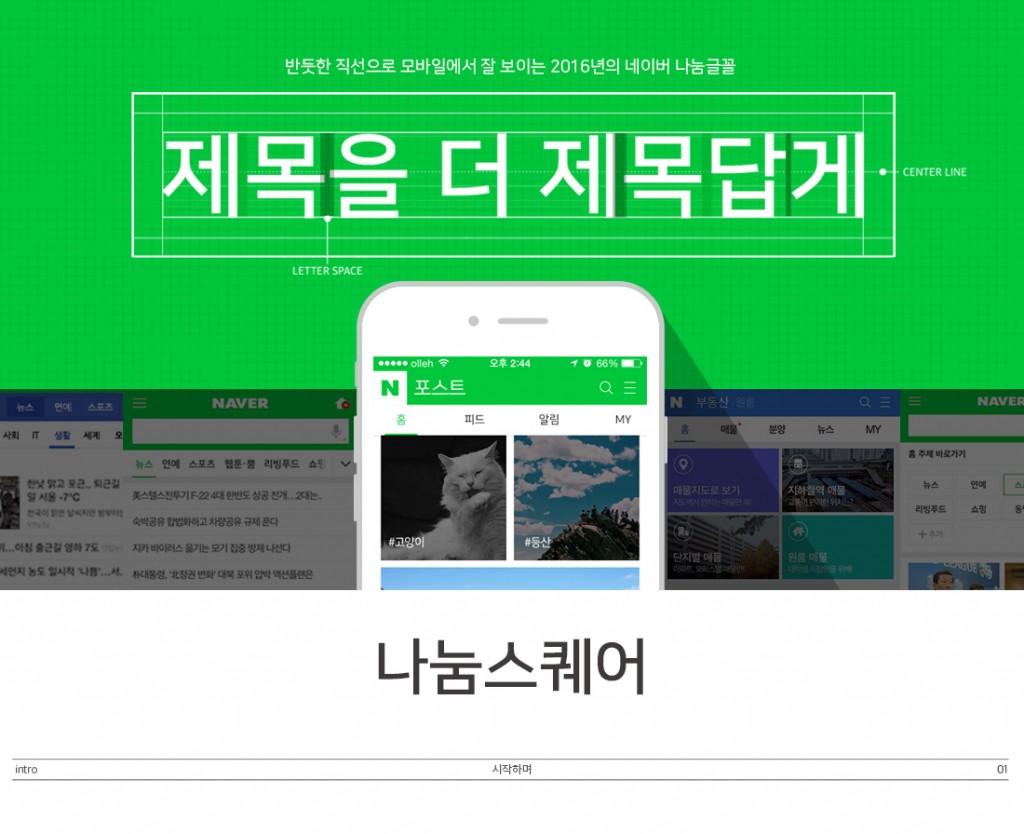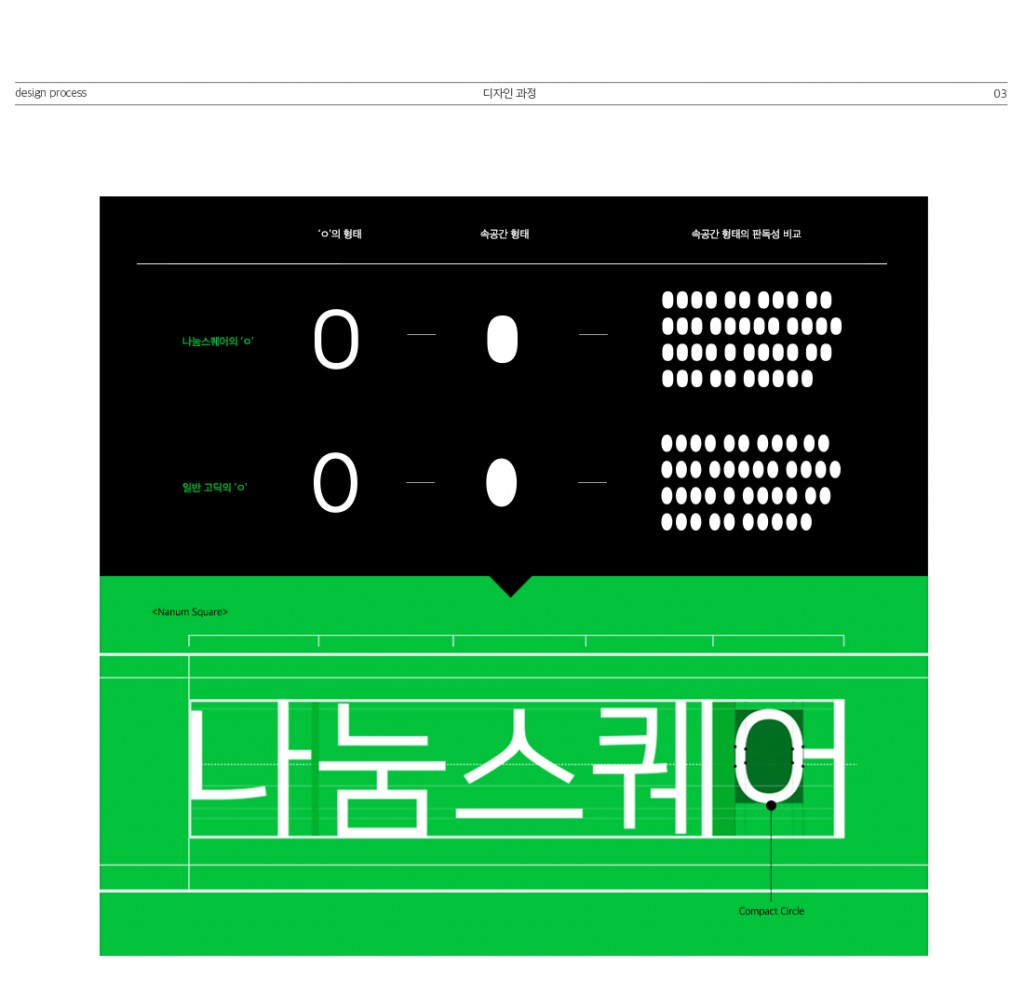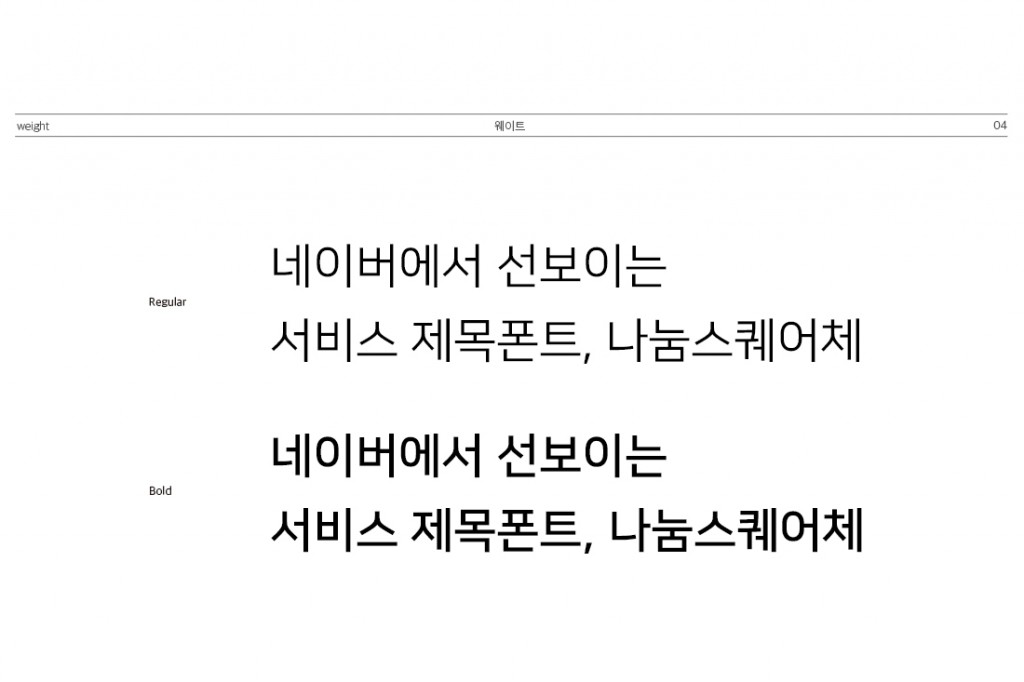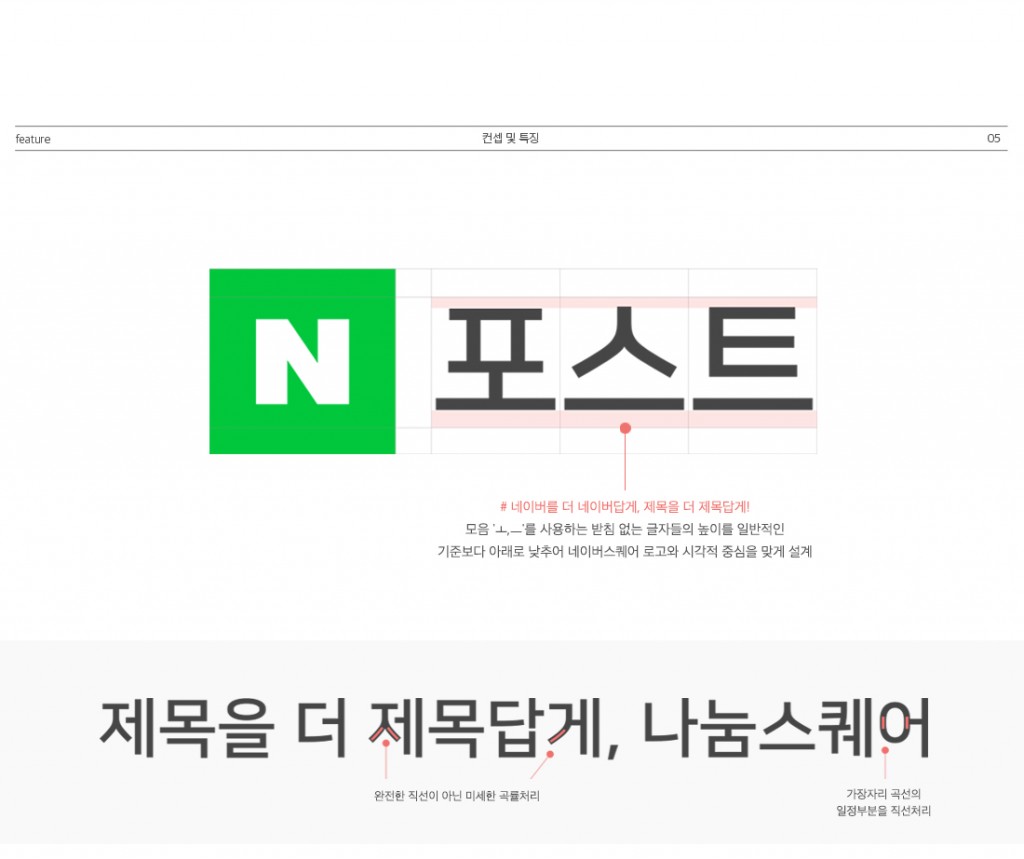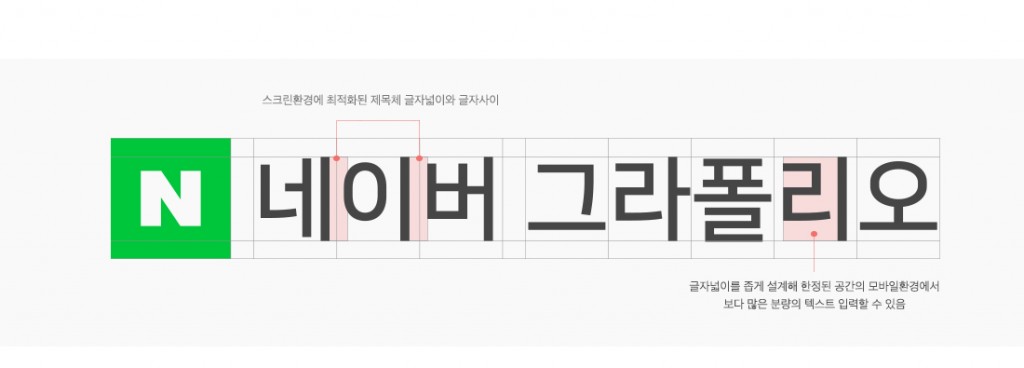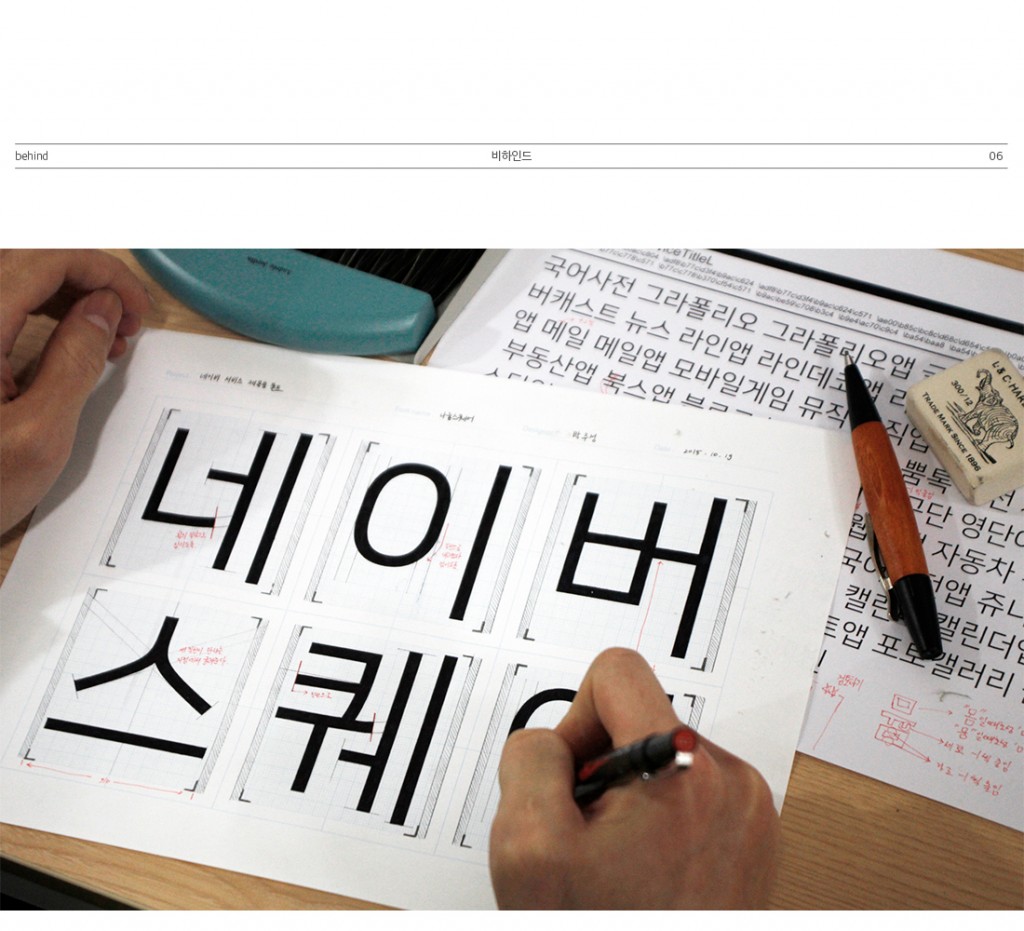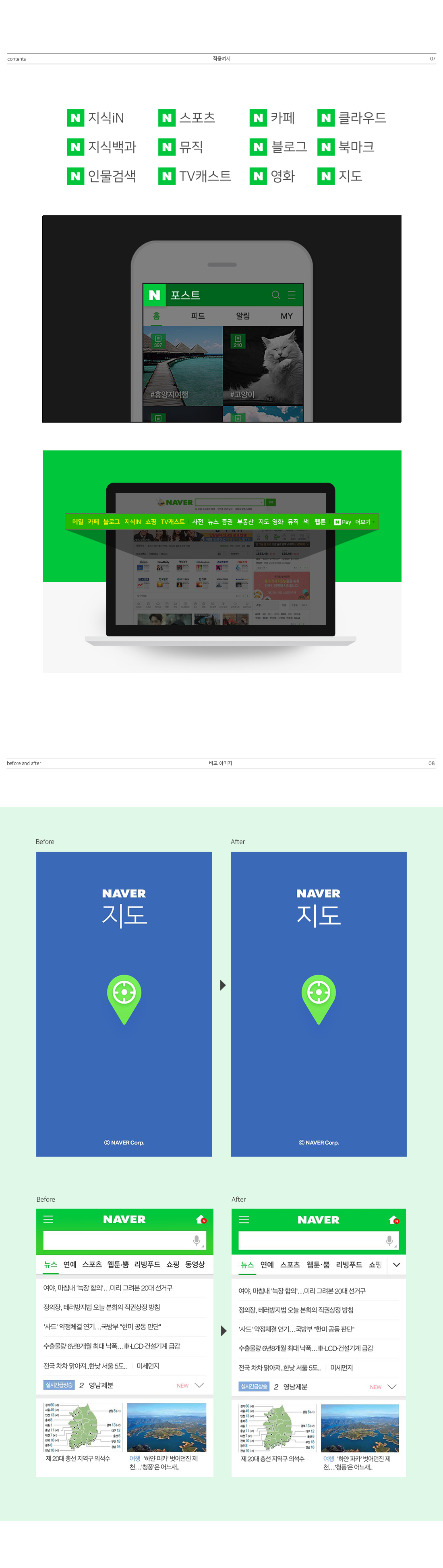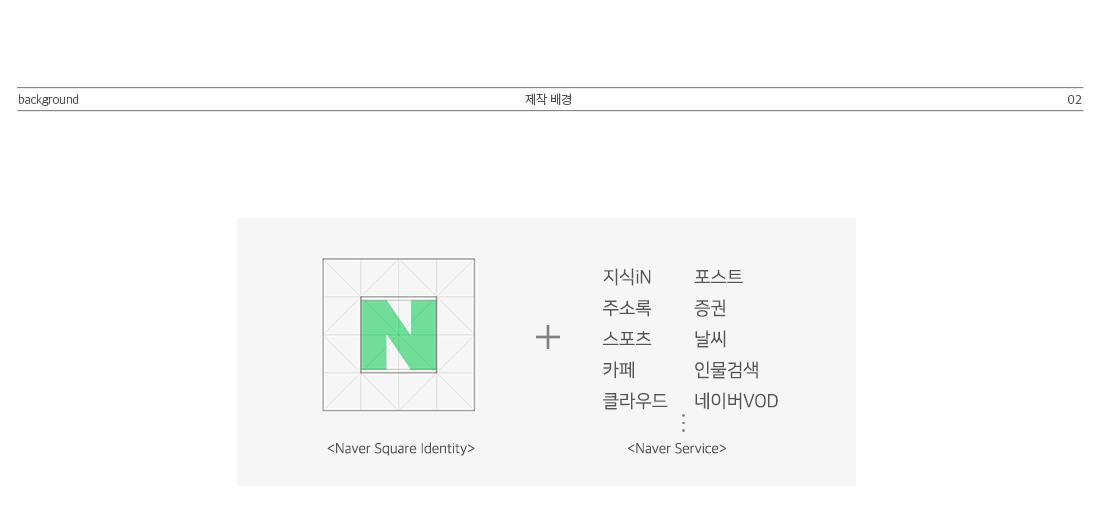
나눔스퀘어 : 네이버의 뉴페이스, 새로운 나눔폰트 탄생!
네이버는 자사를 상징하는 로고인 ‘네이버 스퀘어’에서 출발한 그리드 시스템인 ‘네이버 스퀘어 UX’를 모든 서비스에 적용하고자 하였다. 브랜드 아이덴티티 강화와 일관된 사용자 경험을 제공하기 위해선 필수적이었다. 여기에서 네이버 나눔스퀘어가 시작되었다.
한국의 대표 포털사이트, 네이버. 국내 스마트폰 사용인구의 95% 이상이 네이버를 사용하고 있으며, 모바일로 제공되는 서비스가 무려 110개가 넘는다. 어마어마한 규모다. 문제는 이 수많은 서비스들이 제각각의 레이아웃과 톤&매너를 가지고 따로 논다는 것.
이것이 네이버의 고민이었다. 네이버는 자사를 상징하는 로고인 ‘네이버 스퀘어’에서 출발한 그리드 시스템인 ‘네이버 스퀘어 UX’를 모든 서비스에 적용하고자 하였다. 브랜드 아이덴티티 강화와 일관된 사용자 경험을 제공하기 위해선 필수적이었다. 여기에서 네이버 나눔스퀘어가 시작되었다.
제작배경
한국을 대표하는 포털사이트답게, 네이버는 2008년부터 매년 새로운 글꼴을 만들어 무료로 배포하고 있다. 그것이 바로 ‘한글한글아름답게’라는 공익캠페인으로 여러분이 사용하는 나눔글꼴 시리즈이다. 이 프로젝트 또한 ‘나눔스퀘어’라는 이름으로 2016년의 나눔글꼴로 배포되는 것을 고려하고 제작되었다.
네이버의 제각각 다른 서비스들을 하나의 서체로 통일하는 과정에서 ‘네이버 스퀘어’라는 아이덴티티를 잘 담아내는 것이 가장 중요했고, 이와 더불어 모바일 환경에서 사용되는 것을 고려하여 작은 화면에서도 잘 보이게 제작해야 했다.
디자인과정
네이버에게 가장 필요한 것은 웹과 모바일 환경에서 잘 보이는 폰트였고, 특히 트래픽의 대부분이 모바일로 바뀌고 있는 시기였다. 모바일 디바이스의 한정된 공간에서는 더 많은 글이 더 잘 읽혀야하기 때문에 부가적 요소가 많이 없고 간결한 폰트가 바람직하다. 너무 장식적이고 두껍거나 자간이 넓은 것은 가독성이 떨어지고 디스플레이에서 제대로 구현되기 힘들다.
글자의 넓은 속공간은 가독성에 영향을 주는 중요한 요소이다. 닫힌 자소(ㅇ,ㅁ,ㅂ 등)의 속공간을 넓게 확보하면 디스플레이에서 글자를 작게 출력했을 때 픽셀끼리의 뭉침이 덜하게 보인다. 그러나 모바일의 좁은 화면에서 많은 글을 담기 위해서는 글자를 좁게 할 수 밖에 없다. 넓은 속공간과 좁은 글자넓이. 이 상반되는 두가지 요소를 동시에 충족시키기 위해서 컴팩트하면서도 속공간이 넓은 ‘ㅇ’의 형태를 설계했고 일반적인 ‘ㅇ’보다 주목성과 가독성이 개선될 수 있었다. 이것이 제목체의 특징으로 적절하다고 여겨졌고 이를 기준으로 나눔스퀘어의 특징을 만들어나갔다.
컨셉 및 특징
# 뚜렷한 인상의 직선 디자인
잘 보이면서도 아름다운 디자인을 위하여 직선을 적극적으로 사용했고 일반적으로 곡선으로 표현되는 ㄱ,ㅅ,ㅇ 등의 글자에서도 직선적인 인상을 뚜렷하게 확인할 수 있다.
# 디지털 환경에 최적화
네이버의 다양한 서비스를 표기하는 제목체로써 가독성을 최대한 높이기 위하여 글자 속 공간을 충분히 확보하여 작은 글씨도 알아보기 쉽게 하였으며, 글자폭과 글자 사이 역시 이런 목적에 맞게 최적화했다.
비하인드 스토리
네이버 나눔스퀘어는 글자의 곡선적인 요소들을 직선적으로 디자인한 것이 특징으로 ㄱ,ㄲ,ㅅ,ㅆ,ㅈ,ㅊ.ㅋ 등의 글자에서 잘 나타난다. 나눔스퀘어 이전에도 곡선적인 요소들을 직선으로 곧게 편 제목용 서체들이 있긴 했지만, 이 서체들은 곡선을 완전한 직선으로 바꾼 것에 불과한 반면, 나눔스퀘어는 좀 더 디테일하다.
나눔스퀘어의 글자들을 크기를 키워 자세히 보게 되면, 완전한 직선이 아닌 약간의 곡률을 지닌 곡선으로 되어있음을 알 수 있다. 직선처럼 보이지만 곡선의 느낌을 남겨놓아 너무 딱딱하지 않게 표현한 것이다. 이런 디테일한 표현을 2350자의 모든 ㄱ,ㄲ,ㅅ,ㅆ,ㅈ,ㅊ.ㅋ에 하나의 일관된 인상으로 느껴지도록 조화롭게 조정하는 일이 가장 어려웠던 것 같다.
적용예시